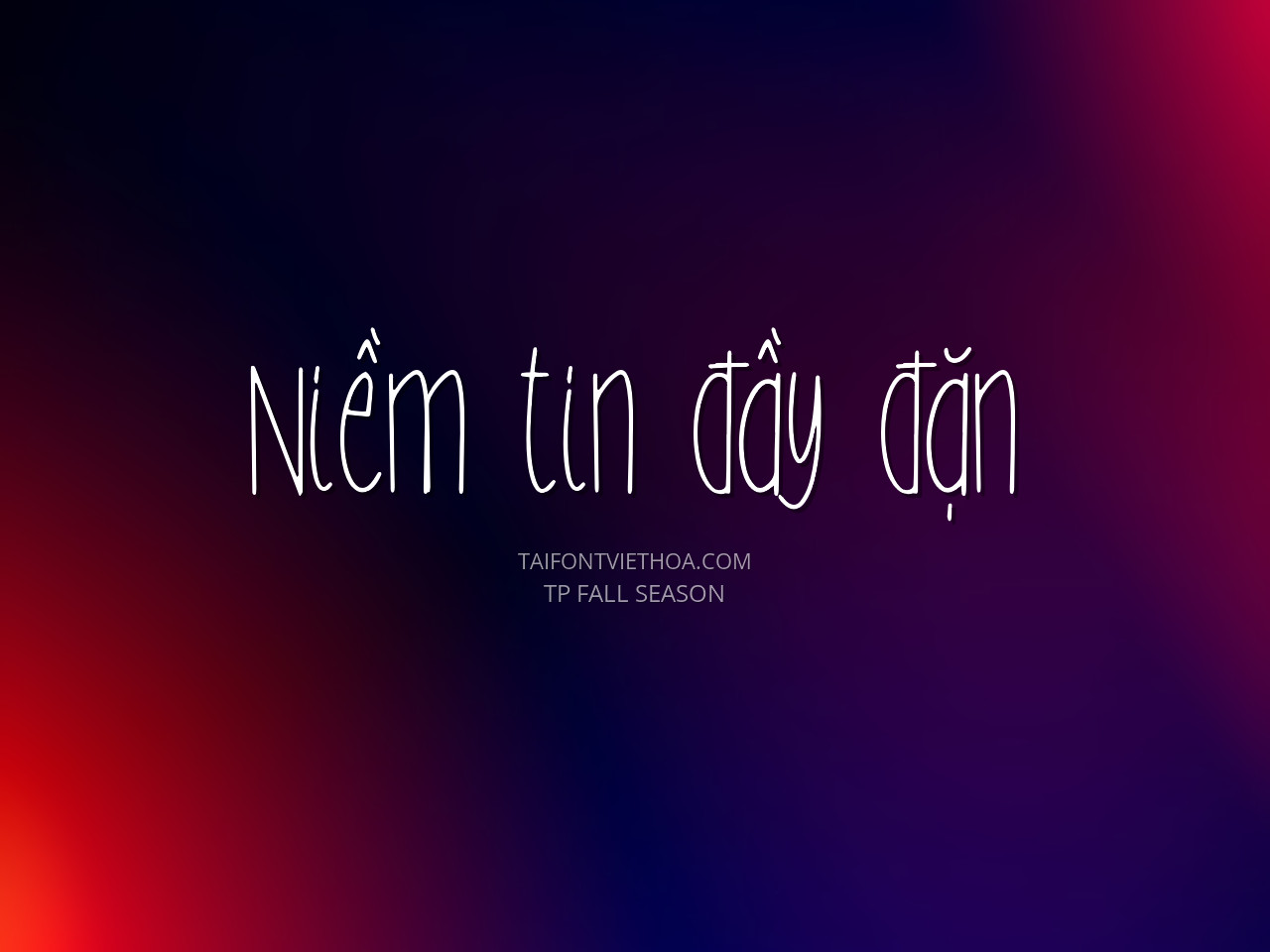
Giới thiệu về font TP Fall Season – Kiểu chữ handwritten ấm áp, mềm mại và tự nhiên
TP Fall Season là phiên bản Việt hóa của font Fall Season – một kiểu chữ handwritten mang phong cách ấm áp, mềm mại và rất tự nhiên. Font được thiết kế với các nét chữ uyển chuyển, nhẹ nhàng và mang cảm giác gần gũi, rất phù hợp cho các dự án thiết kế thiệp, poster, bao bì và các sản phẩm sáng tạo mang phong cách thiên nhiên và mùa thu.
Phiên bản Việt hóa của TP Fall Season đã được Taifontviethoa.comchăm sóc kỹ lưỡng, hỗ trợ đầy đủ dấu tiếng Việt cùng nhiều ngôn ngữ khác. Font giúp các nhà thiết kế dễ dàng áp dụng trong nhiều dự án sáng tạo với phong cách ấm áp, thân thiện và độc đáo.
Thiết kế viết tay mềm mại – Lý tưởng cho thiết kế mùa thu và thiên nhiên
TP Fall Season sở hữu các nét chữ mềm mại, uyển chuyển và bay bổng, tạo nên cảm giác ấm áp, mộc mạc và gần gũi. Font rất phù hợp cho tiêu đề, thiệp mời, poster hoặc các phần thiết kế cần điểm nhấn nhẹ nhàng và tự nhiên. Phong cách thiết kế của Fall Season rất thích hợp với các dự án về mùa thu, thiên nhiên, ẩm thực và truyền thông thân thiện.
Ứng dụng lý tưởng: thiết kế thiệp, poster, bao bì sản phẩm, bài đăng mạng xã hội và các dự án sáng tạo cần phong cách ấm áp, mộc mạc. Ngành nghề phù hợp: mùa thu, thiên nhiên, ẩm thực, truyền thông, quà tặng và thương hiệu thân thiện.